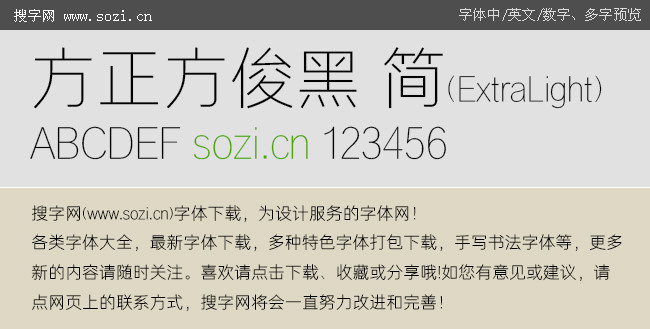
方正方俊黑-簡ExtraLight
搜字網(wǎng)提供一款方正方俊黑簡體中文字體下載,方正方俊黑字體是一款由方正字庫最新開發(fā)的字體,這款字體是在方正俊黑字體的基礎(chǔ)上設(shè)計(jì)而成的,字體整體看上去簡靜優(yōu)雅,筆形簡練,具有很好的視覺效果,適合應(yīng)用于包裝設(shè)計(jì)、平面設(shè)計(jì)、網(wǎng)頁設(shè)計(jì)等應(yīng)用。